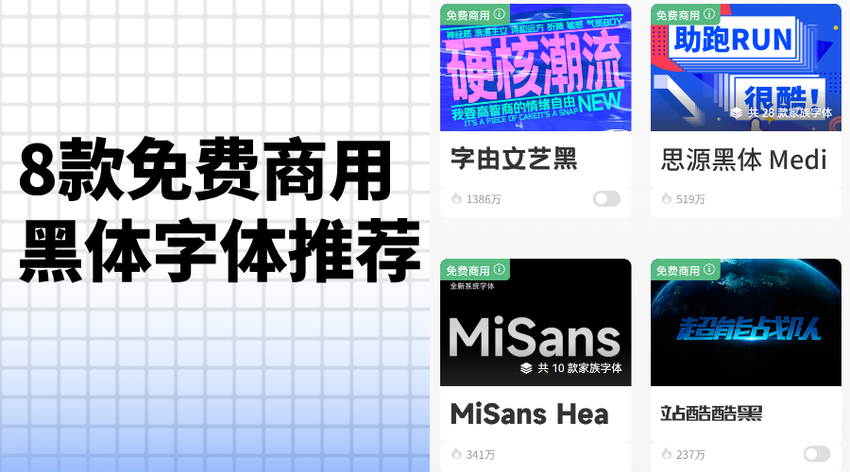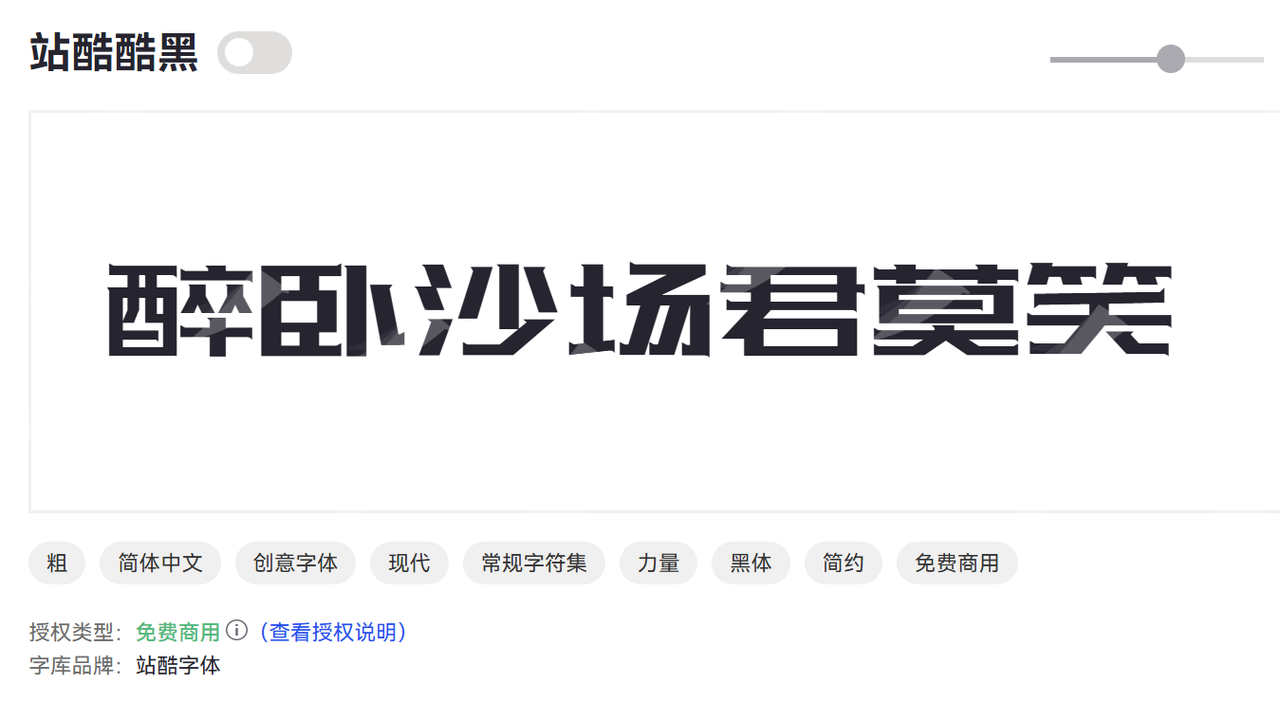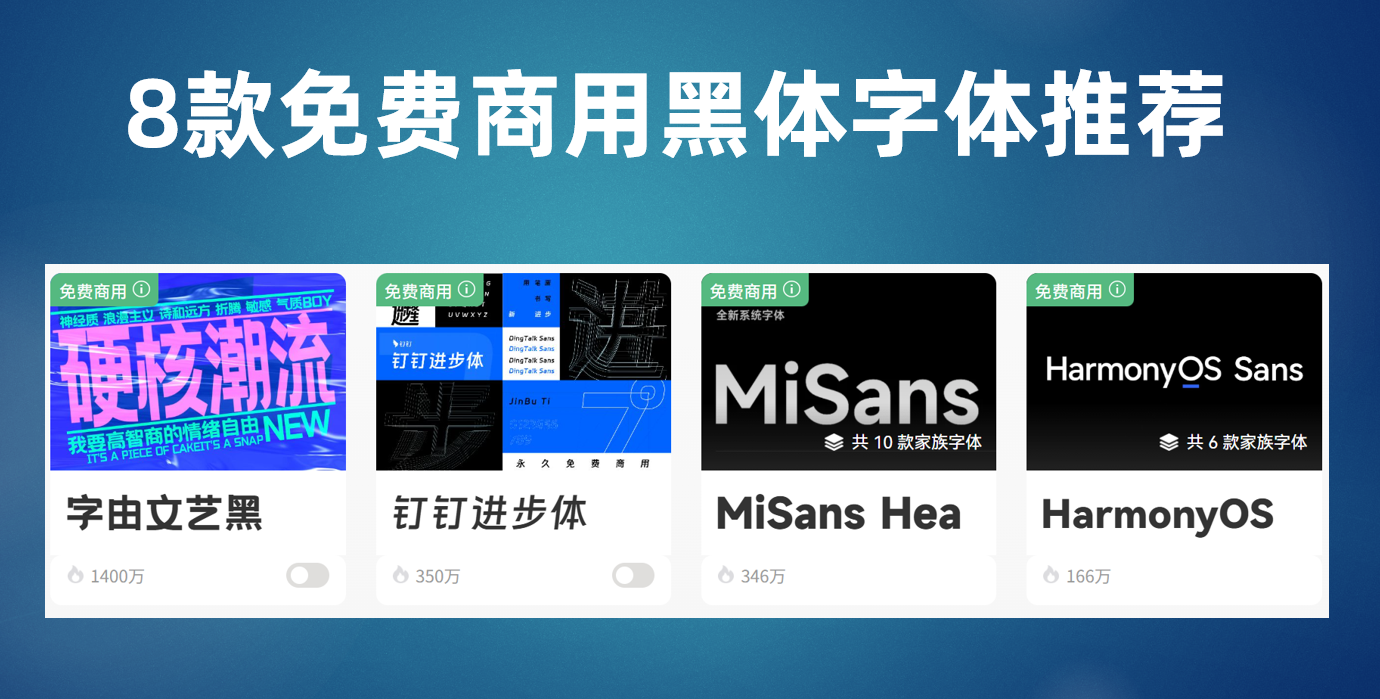
黑体可以商用吗,8款免费商用黑体字体推荐
黑体可以商用吗?黑体是在互联网宣传推广中比较常用的字体,所以很多人比较担心,害怕黑体不可以商用,为自己和公司带来版权的纠纷。黑体其实是一个宽泛的叫法,不是指具体的某一个字体,本文就重点给大家介绍 8 款可以免费商用的黑体字体,让大家在宣传推广中可以放心的使用黑体这一类字体。
一、黑体是什么字体?
黑体是一种无衬线字体,它的特点是笔画粗细均匀,线条端正且没有装饰性的衬线。它的线条简洁,字形方正,视觉效果明快且沉稳。
简单来说,黑体就是我们平常看到的那种“方块字”字体,笔画饱满厚重,没有多余的装饰。黑体的诞生主要是为了对比传统的宋体(有衬线字体),它更适合于标题、标识或需要醒目强调的文字。特别是在现代网页设计、广告设计和公共标识中,黑体的使用频率非常高。这也是为什么我们要给大家推荐免费商用黑体的原因。
二、黑体是否可以商用?
黑体字体的商用问题是很多设计师和运营推广人员最关心的。其实,黑体是一个宽泛的字体类型,它有很多不同的具体字体,不同的黑体字体其版权和授权情况各不相同。
下面就给大家推荐 8 款可以免费商用的黑体字体。
三、8 款可以免费商用的黑体字体
字由文艺黑是字由品牌推出的一款免费黑体字体,这款黑体将图形设计的法则融入黑体设计之中,通过优雅的艺术弧线处理,使字体结构方正饱满,充满张力。
钉钉进步体
钉钉进步体是钉钉以普惠开放的思路,联合汉仪字库,打造一款原创的钉钉品牌字库。这款黑体专门为标题、美术字等场景而生,富有科技活力又兼具书写美感,并且开放给所有个人和组织——永久免费商用,帮助所有人和中小组织放心使用黑体字体进行宣传活动。
思源黑体
思源黑体由Adobe和谷歌联合发布的开源字体,有七种字体粗细(ExtraLight、Light、Normal、Regular、Medium、Bold 和 Heavy),支持中日韩三种语言。它是一款高质量的黑体字体,笔画清晰,视觉舒适。最重要的是,它采用 Open Font License(OFL)授权,允许免费商用。
站酷酷黑
站酷酷黑是在站酷团队在十周年的时候推出的一款黑体字体。这款黑体字形笔画粗犷有力,用宽扁型的字面构建出厚重的字体形态,笔画细节上的修饰既增强了字体的设计感,又让字体多了一些小小的精致感,中宫的饱满使得文字之间的排版组合非常醒目好看。
江城黑体
江城黑的设计灵感源自传统的汉字结构,结合现代的简约风格,旨在提升文字的可读性与美观性。江城黑体广泛应用于各种设计领域,特别是在广告、出版、品牌标识等方面,因其独特的个性和清晰的视觉效果而受到欢迎。
梦源黑体
梦源黑体专为提升视觉传达效果而设计。它的字形轮廓简洁流畅,既保留了传统汉字的美感,又融合了当代设计的时尚元素,适合用于多种领域的排版需求。
水木黑体
水木黑体以简约而富有个性的设计风格而著称。水木黑体将传统汉字的优美线条与现代设计理念相结合,旨在为用户提供清晰且具视觉冲击力的文字展现效果,广泛应用于广告、品牌传播和数字媒体等领域。
文泉驿正黑
总结